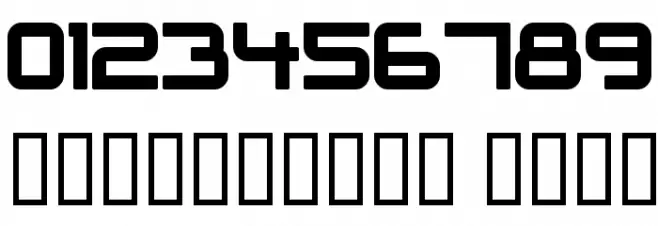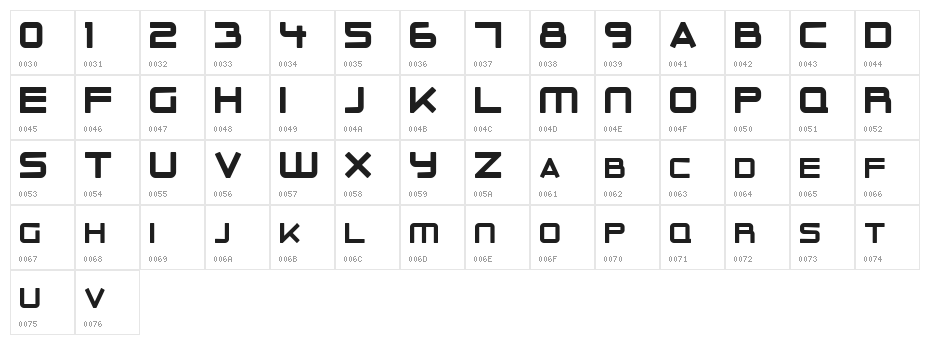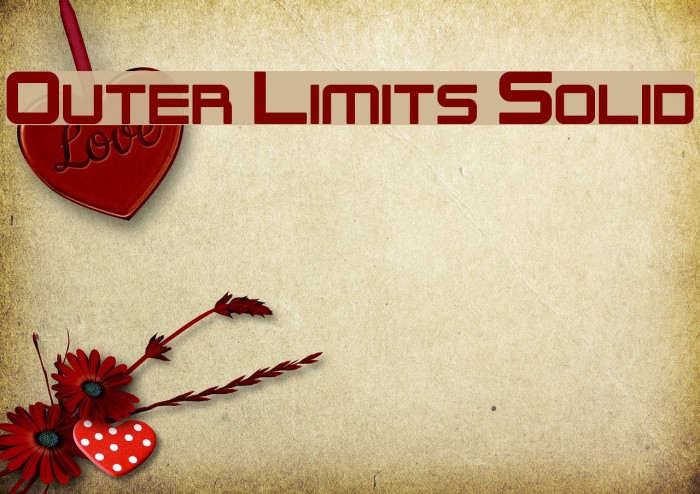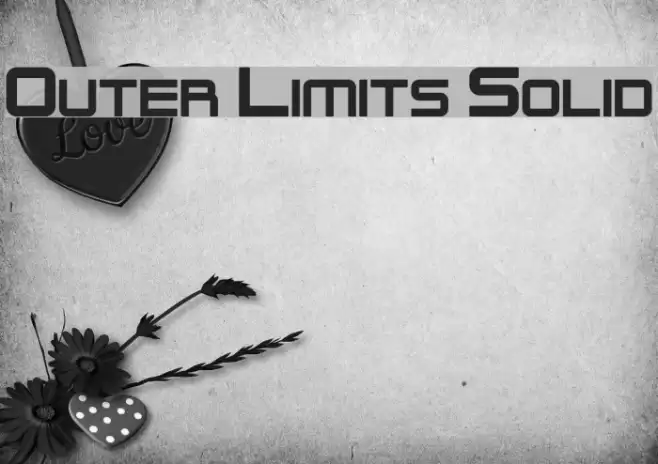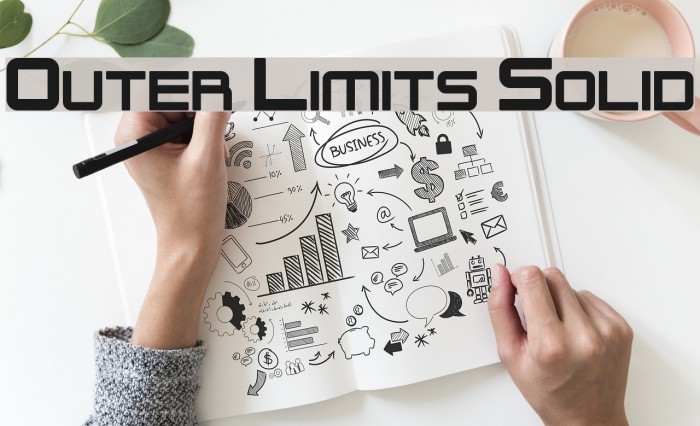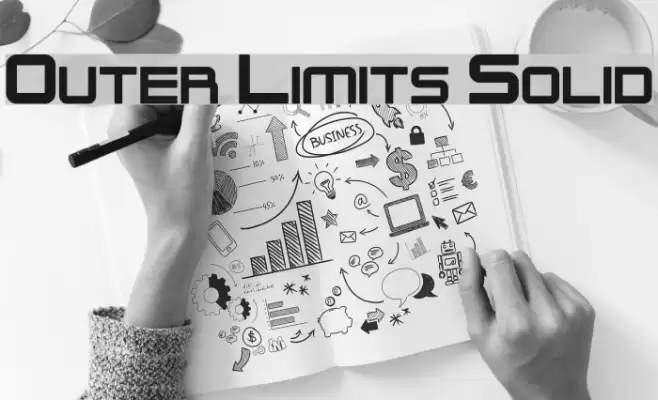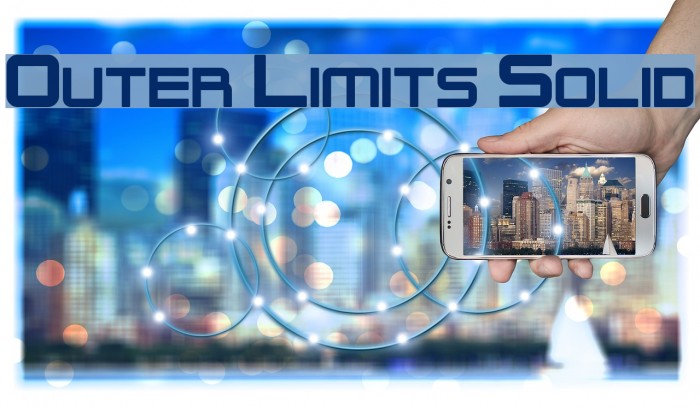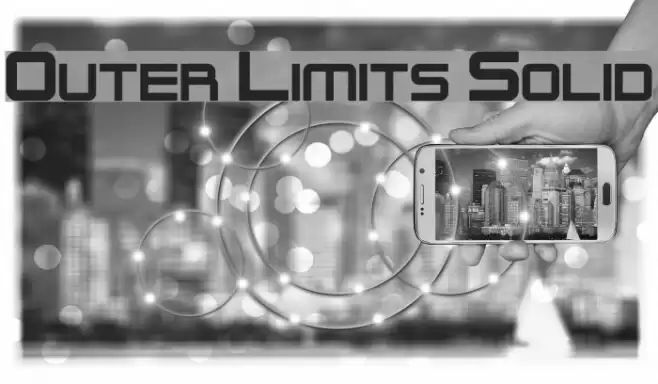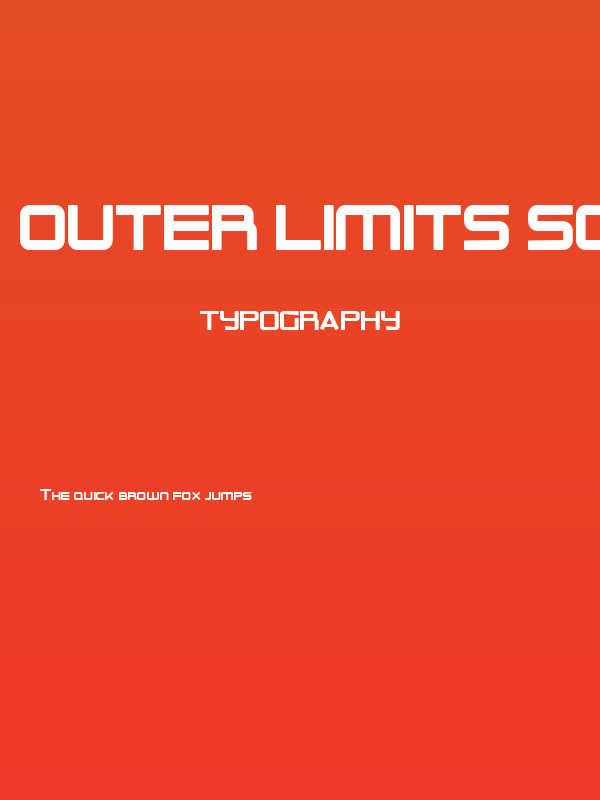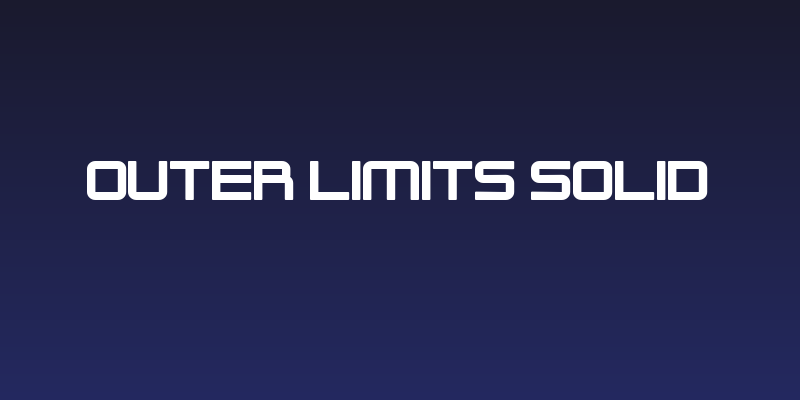
Outer Limits Solid Font
✎ Futuristic
| Vorgeschlagene Projekte | Ideal for sci-fi themed designs, digital interfaces, video game graphics, and tech branding. |